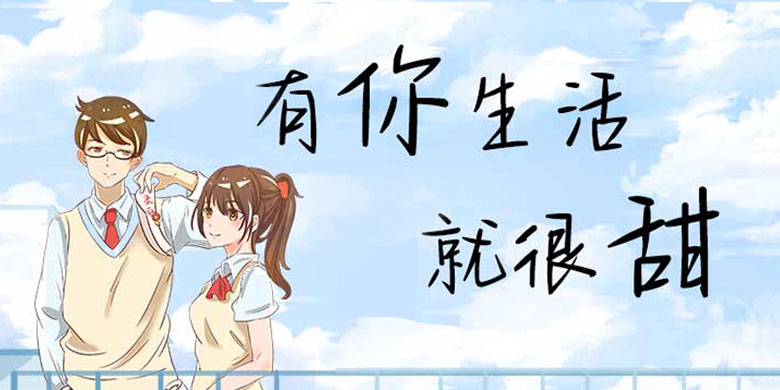
方正手迹-有你生活就很甜
字体品牌: 方正手迹 设计师:刘晔 字体分类:创意书写 字体属性:精品字 字符集:大陆简体(GB2312-80) 发布时间: 2020
有你生活就很甜是一款风格独特的手写体。该字体整体瘦高,笔画平直,转折坚硬果断,干净利落给人爽朗的感觉。适用于文艺类的书刊、品牌广告和产品包装设计,以及社交网络的个性化用字。